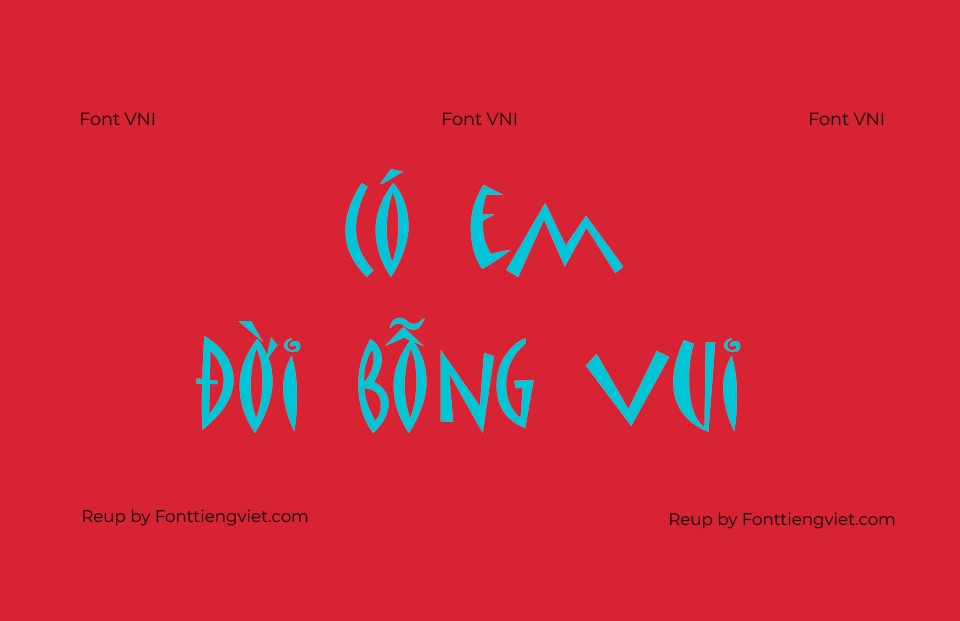
Font Việt hoá VNI Matisse
Giới thiệu về Font Việt hoá VNI Matisse
Trong thế giới đồ họa, việc lựa chọn một bộ Font Miễn Phí chất lượng luôn là ưu tiên hàng đầu của các nhà thiết kế và học sinh. Font Việt hoá VNI Matisse nổi lên như một biểu tượng nghệ thuật đầy tính phá cách, mang đến hơi thở hiện đại xen lẫn nét cổ điển độc đáo. Với những đường nét bay bổng và cấu trúc đặc biệt, bộ font này giúp truyền tải thông điệp một cách ấn tượng, làm nổi bật mọi nội dung từ tiêu đề bài giảng đến các ấn phẩm truyền thông trường học. Việc sử dụng bảng mã VNI quen thuộc giúp người dùng dễ dàng thao tác trên các phần mềm soạn thảo cũ và mới.
Đặc điểm nổi bật của Font Việt hoá VNI Matisse
Phong cách nghệ thuật ấn tượng
Font Việt hoá VNI Matisse sở hữu các đường nét được cách điệu mạnh mẽ, tạo cảm giác như những nét vẽ thủ công tinh tế. Đây là lựa chọn hoàn hảo cho các dự án thiết kế bìa sách, áp phích sự kiện hoặc làm tiêu đề cho các bài thuyết trình sáng tạo. Font chữ này không chỉ đảm bảo tính thẩm mỹ mà còn giữ được độ nhận diện ký tự tốt, giúp người xem dễ dàng tiếp nhận thông tin mà không gây rối mắt.
Khả năng ứng dụng linh hoạt
Dù bạn là một giáo viên cần làm slide bài giảng sinh động hay một bạn học sinh đang thiết kế tờ rơi cho câu lạc bộ, Font Việt hoá VNI Matisse đều đáp ứng tốt. Sự kết hợp giữa nét thanh và nét đậm trong font tạo nên một nhịp điệu thị giác lôi cuốn, phù hợp với nhiều chủ đề từ giáo dục đến nghệ thuật giải trí.